《九层妖塔》7个字侵权,赔偿14万!别再瞎用商业字体了…
“老板,这个字体不能商用!”
“没事啊,不会有人知道的啦,浪费那个钱”
好吧!事情闹大了 7个字14万。
2015年9月,灾难探险片《九层妖塔》上映,20天取得了超过6亿的票房,并斩获多项大奖。
不过,这部电影惹的官司也不少,继著作权、插曲的侵权诉讼外,这部电影中的道具还涉及字体侵权。
大家是不是都会以为标题字体?
错了!!!
其实是在电影里面出现了一本书和一张旧报纸!!!
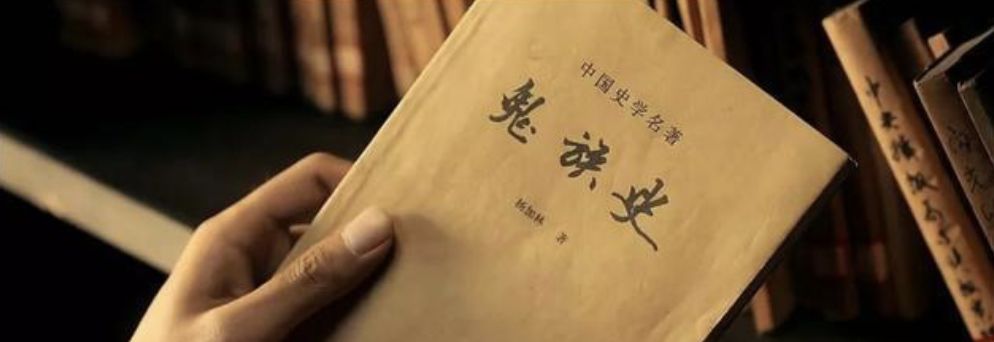
《九层妖塔》中的剧照
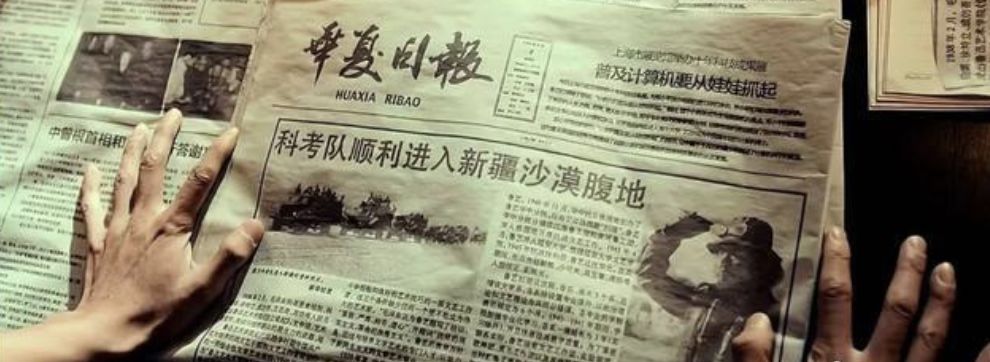
《九层妖塔》中的剧照
向佳红毛笔行书字体:
早在2013年12月,向佳红向广东省版权局申请作品名称为“向佳红毛笔行书字体”的作品著作权登记。他已在此套字体库中明确署名此套字体仅用于学习交流使用,商业使用需经其授权,同时留有其联系方式。
电影《九层妖塔》上映后,向佳红发现在该电影出现的道具《鬼族史》图书、《华夏日报》报纸上使用了他的书法作品“鬼”、“族”、“史”、“华”、“夏”、“日”、“报”。他认为,影片的制作、发行、投资和传播方未经过他许可,也未署名,侵犯了他对上述书法作品享有的署名权、复制权。
大家对比一下
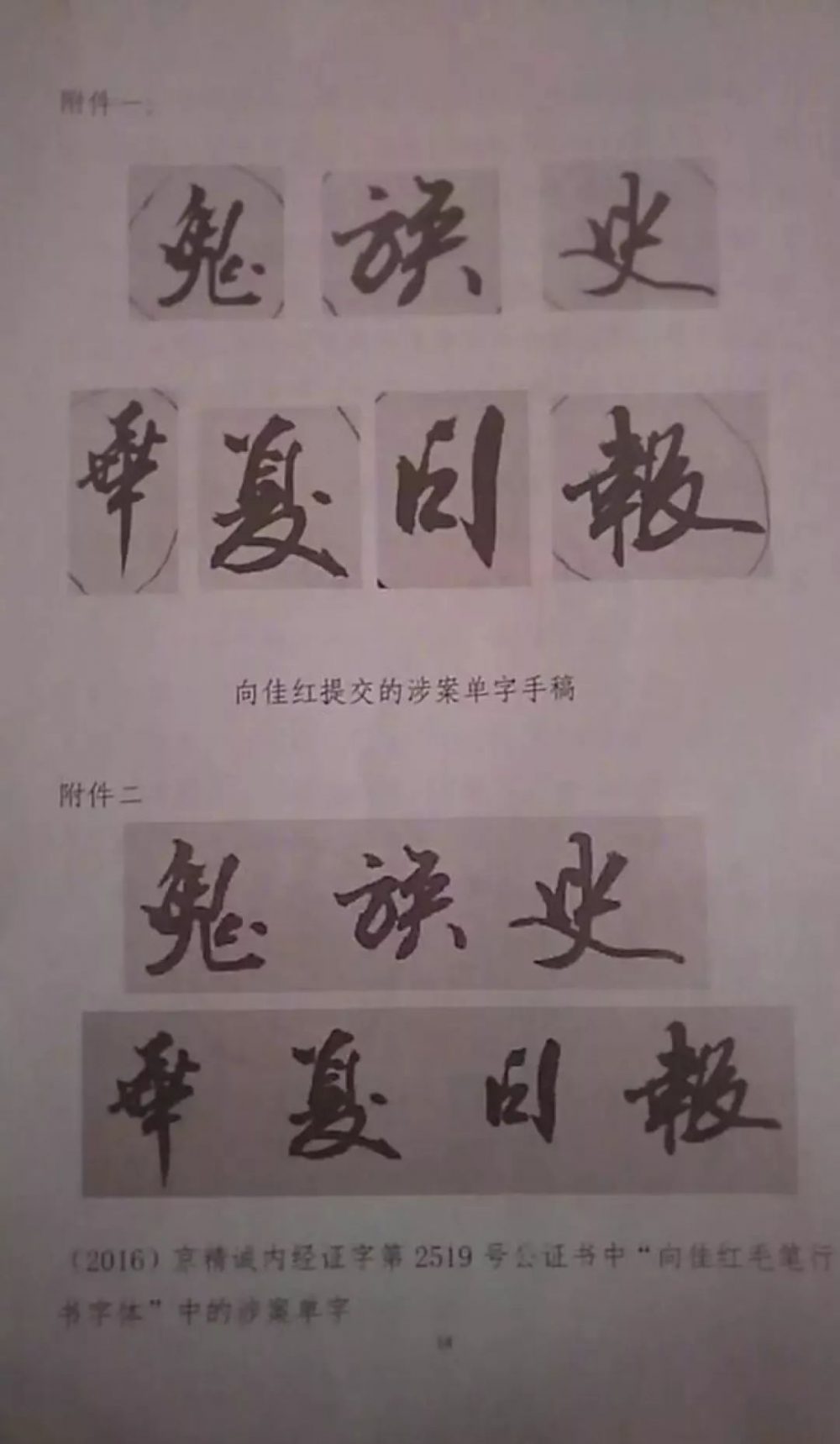
上图为涉嫌抄袭字/下图为版权字
真的是一毛一样!!!
北京市朝阳区法院审理认为:书法的书写虽然受限于汉字本身笔画和结构上的固定搭配,但书写者仍借助具体的线条、点画等,在字形结构、偏旁部首比例、笔画长短、粗细选择、曲直设计等诸多方面进行调整和创造,融入自己的选择和判断,表现出独特艺术美感,体现出书写者自己的个性,从而具有符合著作权法要求的独创性,成为著作权法保护的美术作品。
本案中,向佳红主张权利的“鬼”、“族”、“史”、“华”、“夏”、“日”、“报”7个单字在断笔方式,布局结构,笔画粗细、曲直、长短以及繁简字组合等方面均体现出了独特的艺术美感,呈现出了不同于传统行书及其他常见字体的独创性表达,融入了书写者独特的智力判断和选择,属于著作权法规定的美术作品。
经对比,电影及预告片的道具使用的7个单字与向佳红涉案单字在字形整体结构,偏旁部首比例,笔画的长短、粗细、曲直选择等方面均无明显区别,可认定这7个单字是向佳红的7幅书法作品。
在电影作品和以类似摄制电影的方法创作的作品中,制片者通常会以片头、片头字幕或屏幕标注等方式为作者署名。四被告在使用涉案书法作品时未以适当方式表明向佳红是该作品的作者,侵害了其署名权。同时,法院认为4被告使用涉案单字的行为不属于合理使用。
结果:日前,法院一审判决4被告在判决生效之日起30日内履行在报纸上登载声明的义务,向原告公开赔礼道歉,共同赔偿向佳红14万元。
所以设计师用字需要注意了!
非常非常多字体不能用于商业。
不然律师函要到了。
乱用字体。